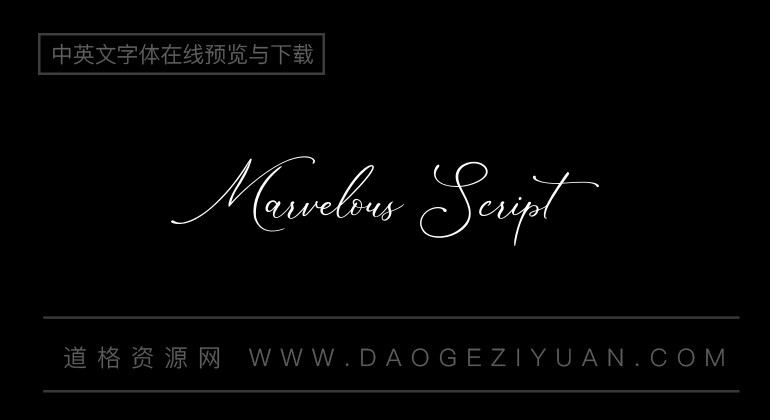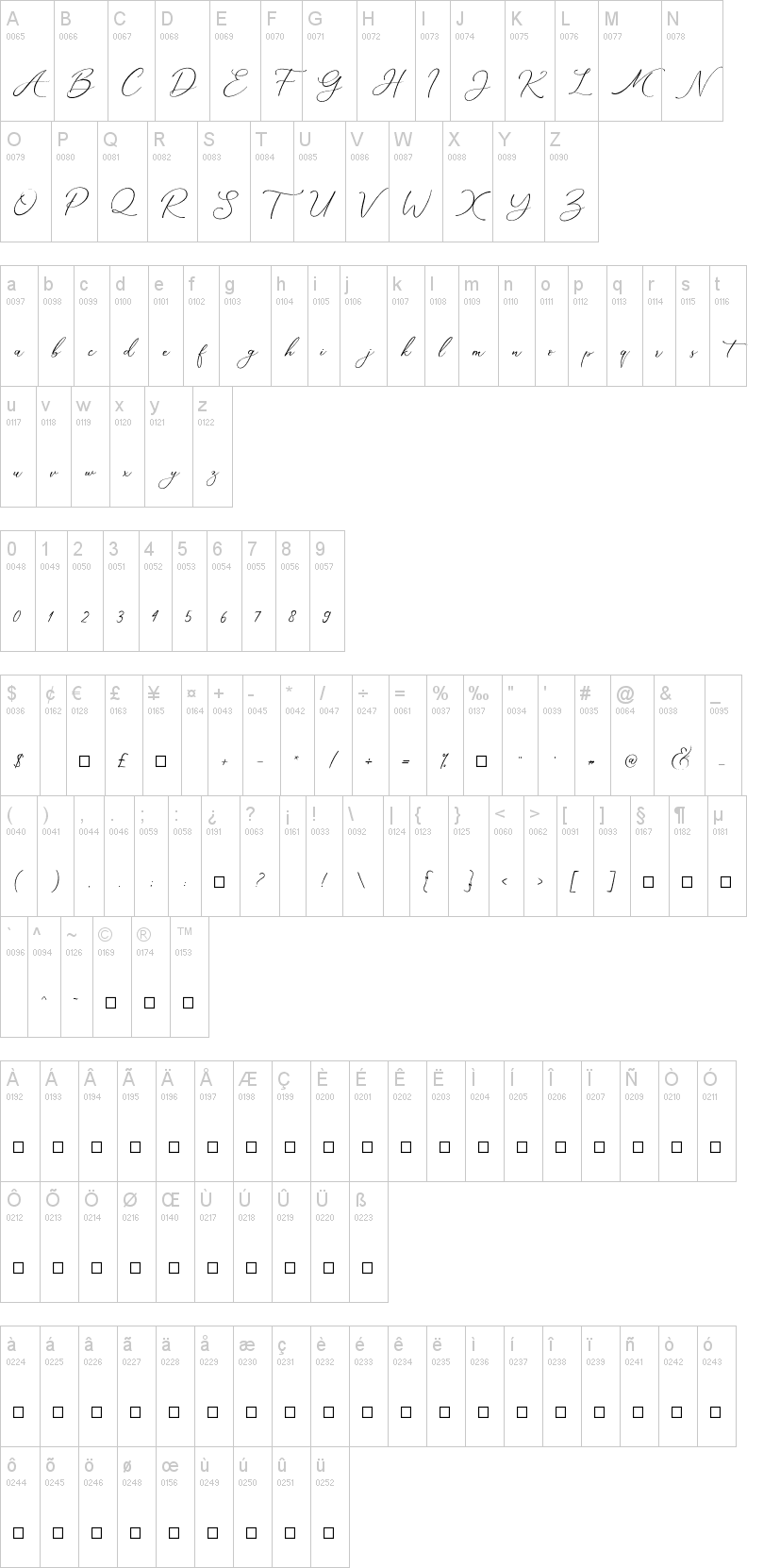
Marvelous Script
? Marvelous Script 是一款美式手写体字体,受到美国手写体字体的启发而设计,具有自然、灵动的线条,表现出美国手写体字体的自然、灵动、活泼的特点。它有着温柔的曲线,以及深沉又富有表现力的节奏感,非常适合用于现代设计中。它可以用于各种商业设计项目,如品牌设计、海报设计、包装设计等,也可以用于印刷设计,如书籍、杂志等。
Marvelous Script是一款非常不错的手写艺术字体,具有很好的视觉感,适合于文化类的宣传设计、商业类品牌的广告和产品包装设计以及个性化文字排版等较多场景。